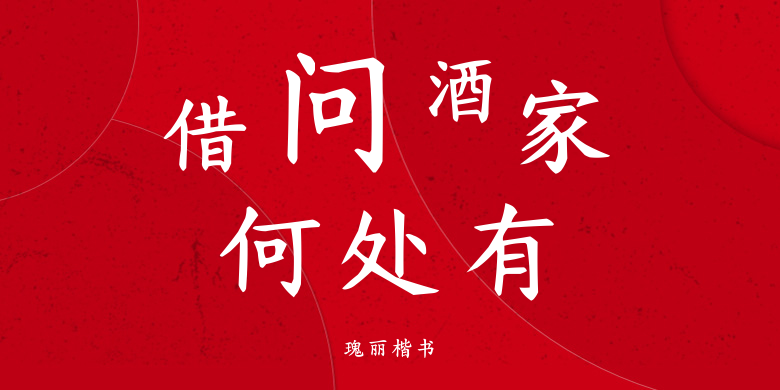
瑰丽楷书
瑰丽楷书,这款字体结构工整、笔画清晰,兼顾美观与易读性,适用于标题、正文、海报、包装、LOGO 等多种场景。字形优雅稳定,风格百搭耐看,适配日常排版与创意设计,让文字呈现更舒适、更具质感。瑰丽楷书一笔一画,皆是细节,以均衡的比例、流畅的线条打造舒适视觉体验,字形端正大气,风格简约现代。无论是商业设计、品牌宣传还是日常排版,都能轻松驾驭,让文字更有格调与力量。瑰丽楷书字体下载。